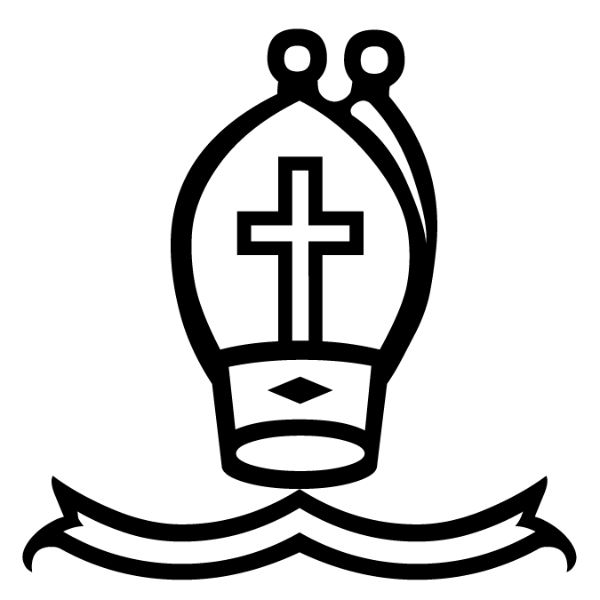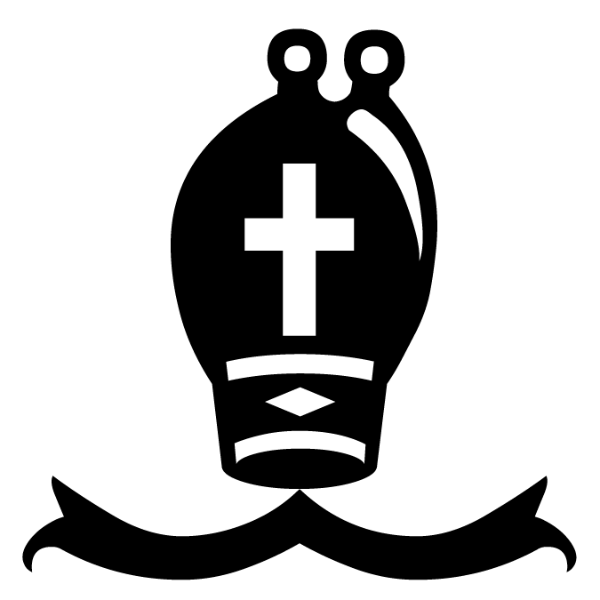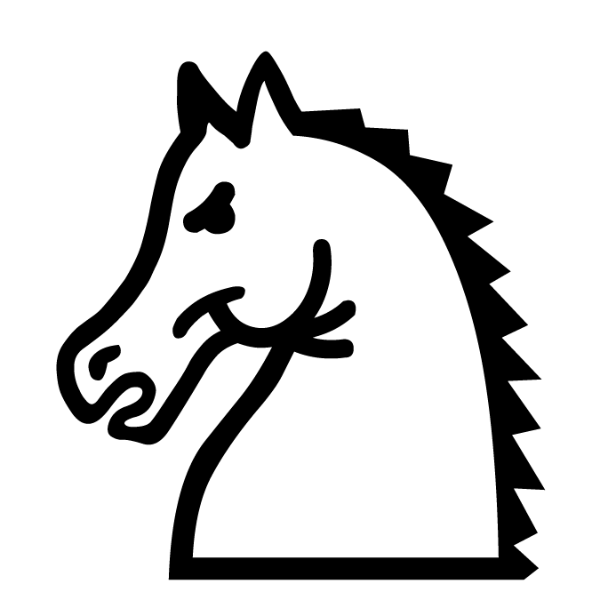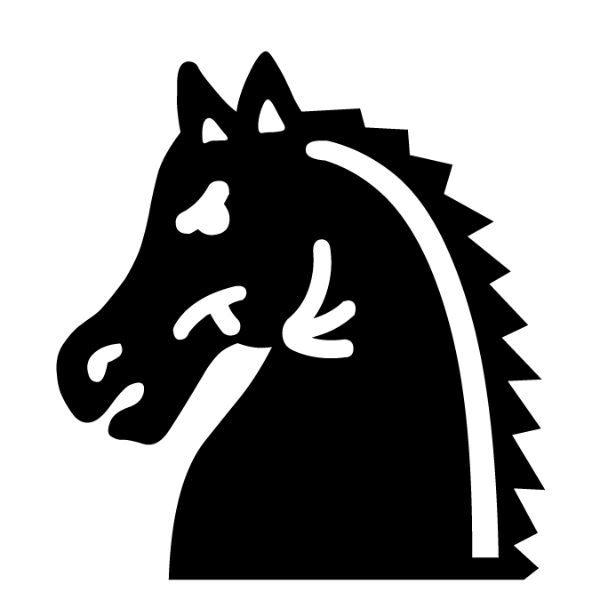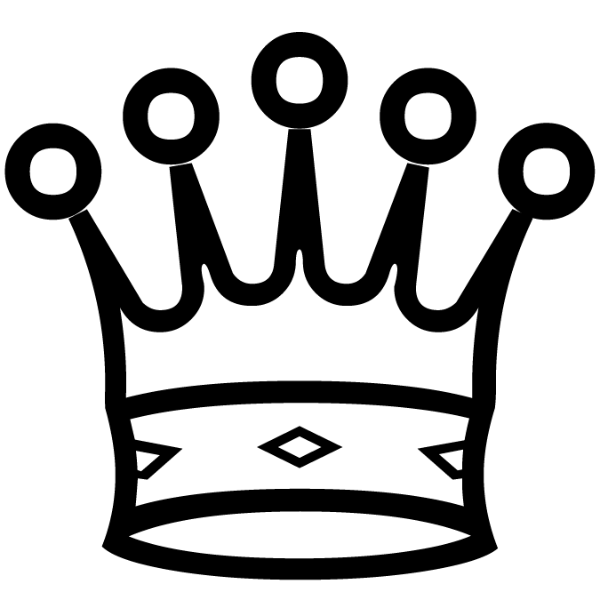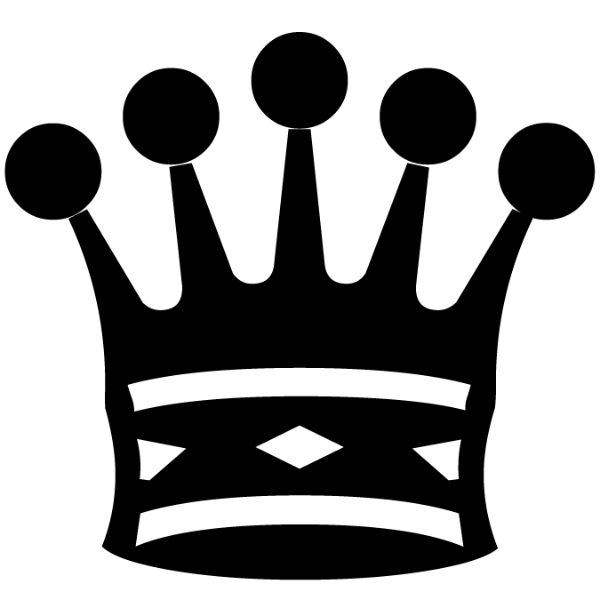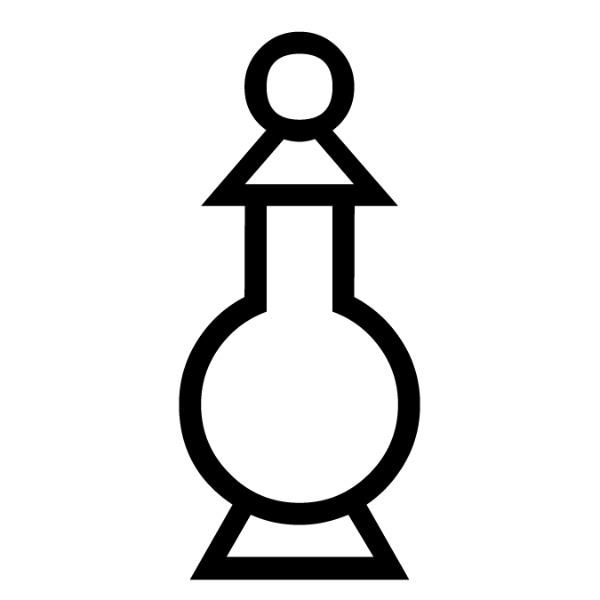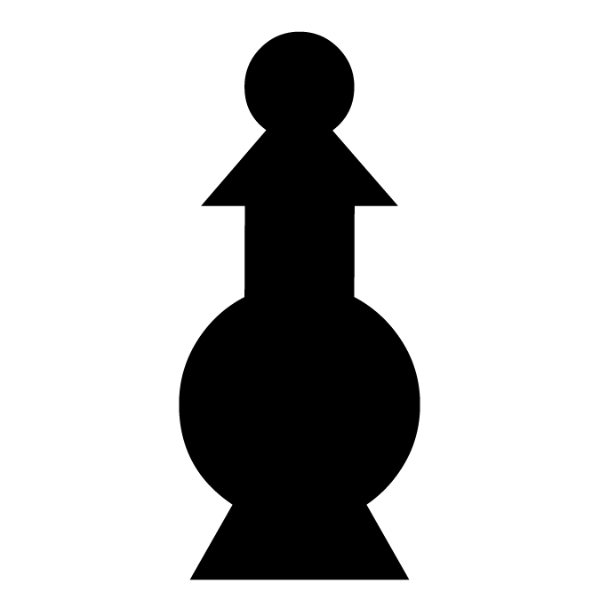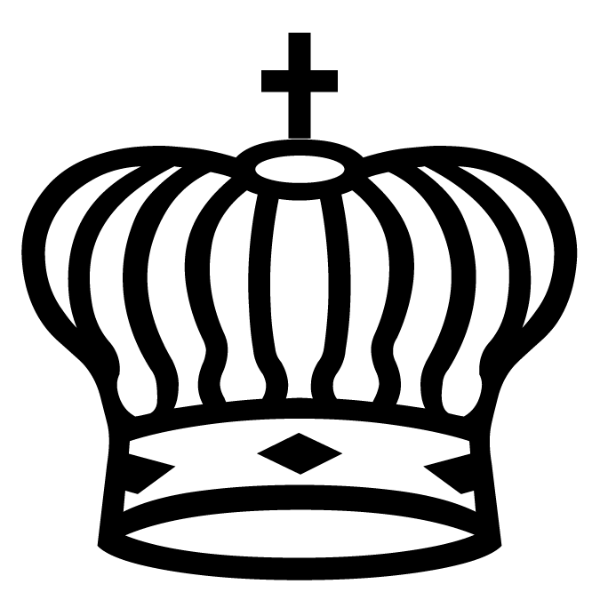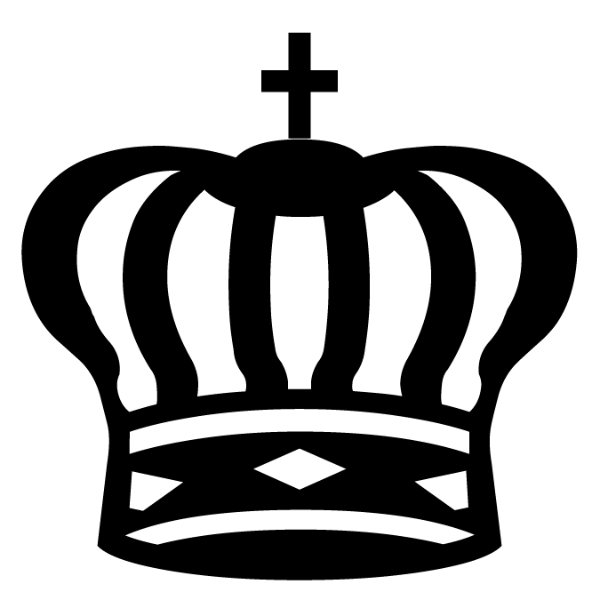
Descarga la fuente de ajedrez «Chess Kingdom», una tipografía especialmente estilizada con un diseño distintivo que destaca la corona del Rey. Esta fuente de ajedrez Freeware fue creada por Armando Hernández Marroquín. Puedes descargarla, instalarla y utilizarla en tu ordenador para personalizar documentos, diseños o proyectos relacionados con el ajedrez.
Prueba el Juego de Ajedrez con la Fuente Kingdom: